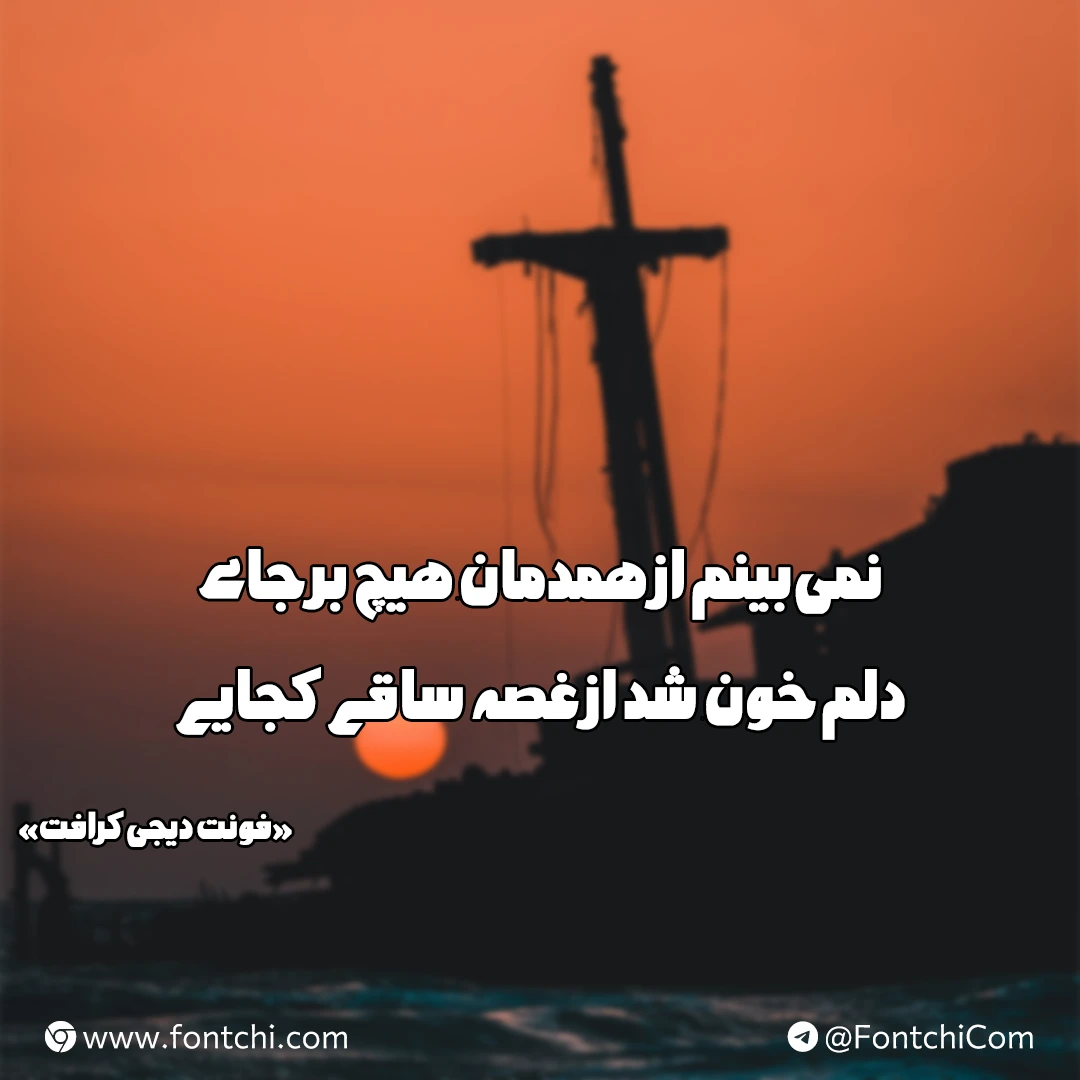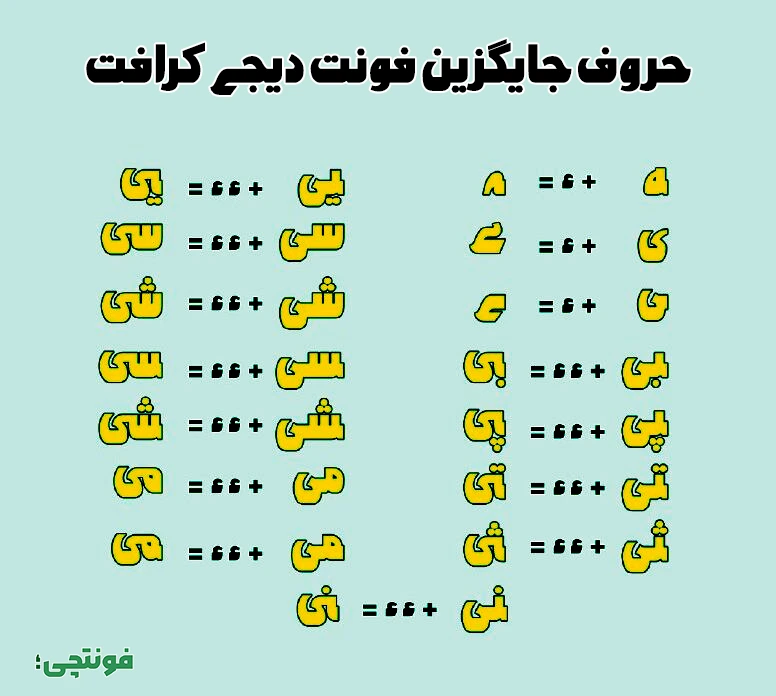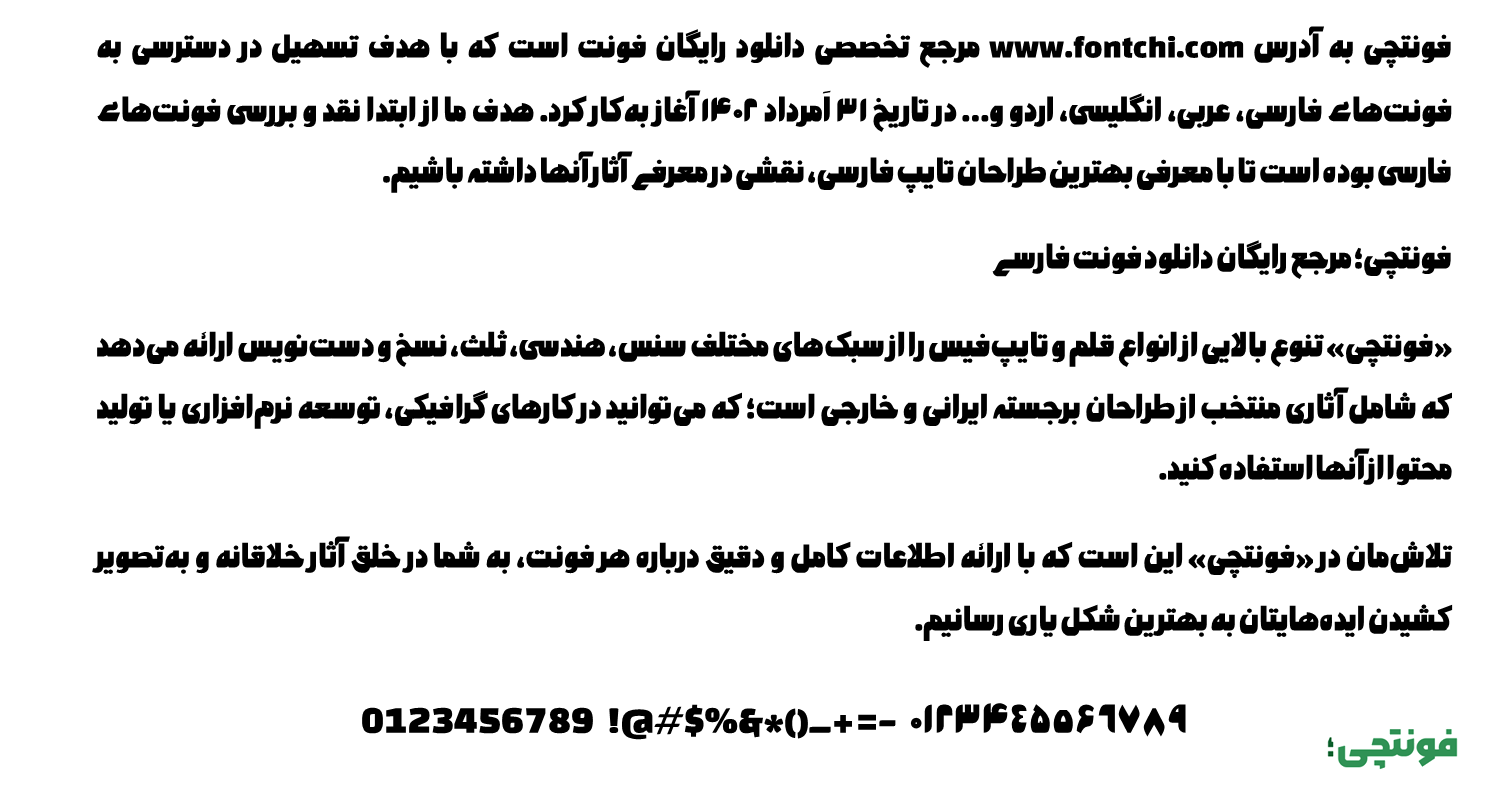
فونت دیجی کرافت (Digi Craft)
فونت دیجی کرافت (به انگلیسی: Digi Craft) قلمی مناسب برای عناوین و تبلیغات است که با وزن فوق سنگین Ultra Black با ضخامت بالایی طراحی شده است. از این فونت ضخیم می‌توانید در پروژه‌های تبلیغاتی و کارهای نمایشی که نیاز به جلب توجه دارند استفاده کنید.
فونت رایگان دیجی کرافت توسط مهدی برقگیر طراحی شده است که از حروف جایگزین متعددی برای نمایشی‌تر کردن این قلم نیز پشتیبانی می‌کند. در ادامه با نقد و بررسی این فونت همراهتان هستیم.
فونت دیجی کرافت یک فونت فوق سنگین با ظاهری سیاه است که برای متون کوتاه و عناوین کاربرد دارد. این فونت فارسی از زبان‌های دیگری نظیر عربی، انگلیسی و کوردی نیز با همین سبک ضخیم خود پشتیبانی می‌کند. کاراکترهای خاص، اعراب و گلیف‌های تزئینی در هم‌نشینی خوبی با این قلم قرار دارند که ظاهر آن را نمایشی می‌کند.
در بخش اعداد این قلم برخلاف سایر فونت‌های سری دیجی، شاهد پشتیبانی از اعداد فارسی و عربی هستیم. به‌طوری که اعداد عربی «۴۵۶» دارای گلیف اختصاصی خود در مقایسه با اعداد فارسی «۴۵۶» هستند.
ظاهر سیاه و ضخیم این قلم آن را به گزینه مناسبی برای کارهای نمایشی و گرافیکی که دارای افکت سه‌بعدی هستند تبدیل کرده است. از جمله:
• چاپ بیلبوردها و بنرهای تبلیغاتی.
• چاپ روی عنوان کتاب و مجلات.
• طراحی لوگو تایپ و پوسترهای تاکیدی.
• استوری، پست و تامنیل پست شبکه‌های اجتماعی.
• استفاده در عکس نوشته‌ها، جملات قصار و جملات تاکیدی.
حروف جایگزین فونت دیجی کرافت
در این فونت شاهد پشتیبانی از حروف جایگزین متنوعی برای حروف و ترکیباتی همچون «ه، ی، بی، پی، تی، ثی، یی، سی، شی، می، نی» هستیم.
مطابق با تصویر بالا می‌توانید با افزودن تعداد یکی یا دوتایی از کاراکتر «ء» به انتهای ترکیبات فوق، امکان تایپ متفاوت برخی ترکیبات را داشته باشید. این ترکیبات به نمایشی‌تر کردن و تاکید روی برخی اصطلاح کلمات کمک می‌کند که در فونت‌های عناوین با جنبه تبلیغاتی و تاکیدی اهمیت دارد.